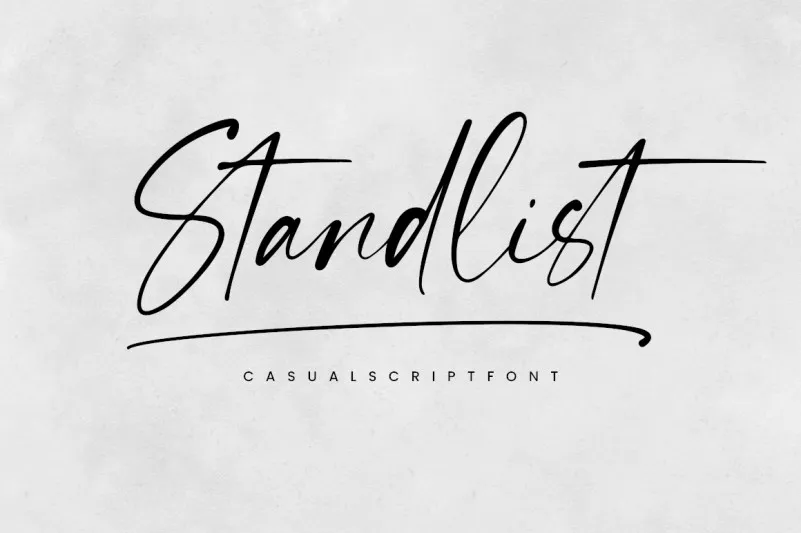
A Standlist Font é uma criativa seleção para designers que buscam uma fonte script moderna e divertida. Criada pela RasdiType, esta fonte abraça a essência orgânica de um autêntico traço humano, mas incorpora um toque contemporâneo e vibrante. Com seus traços finos e lisos, a Standlist é perfeita para adicionar uma pitada única a qualquer projeto gráfico. Este design PUA (Portable User Access) permite que você facilmente manipule todos os sinais e swashes da fonte, sem ter que preocupar-se com compatibilidade ou complexidade. Seja um logotipo minimalista, cartão de visita colorido ou uma página web dinâmica, a Standlist está aqui para te ajudar a alcançar o próximo nível em sua arte digital. Experimente a Standlist Font e faça seu design soar ainda mais criativo e único.